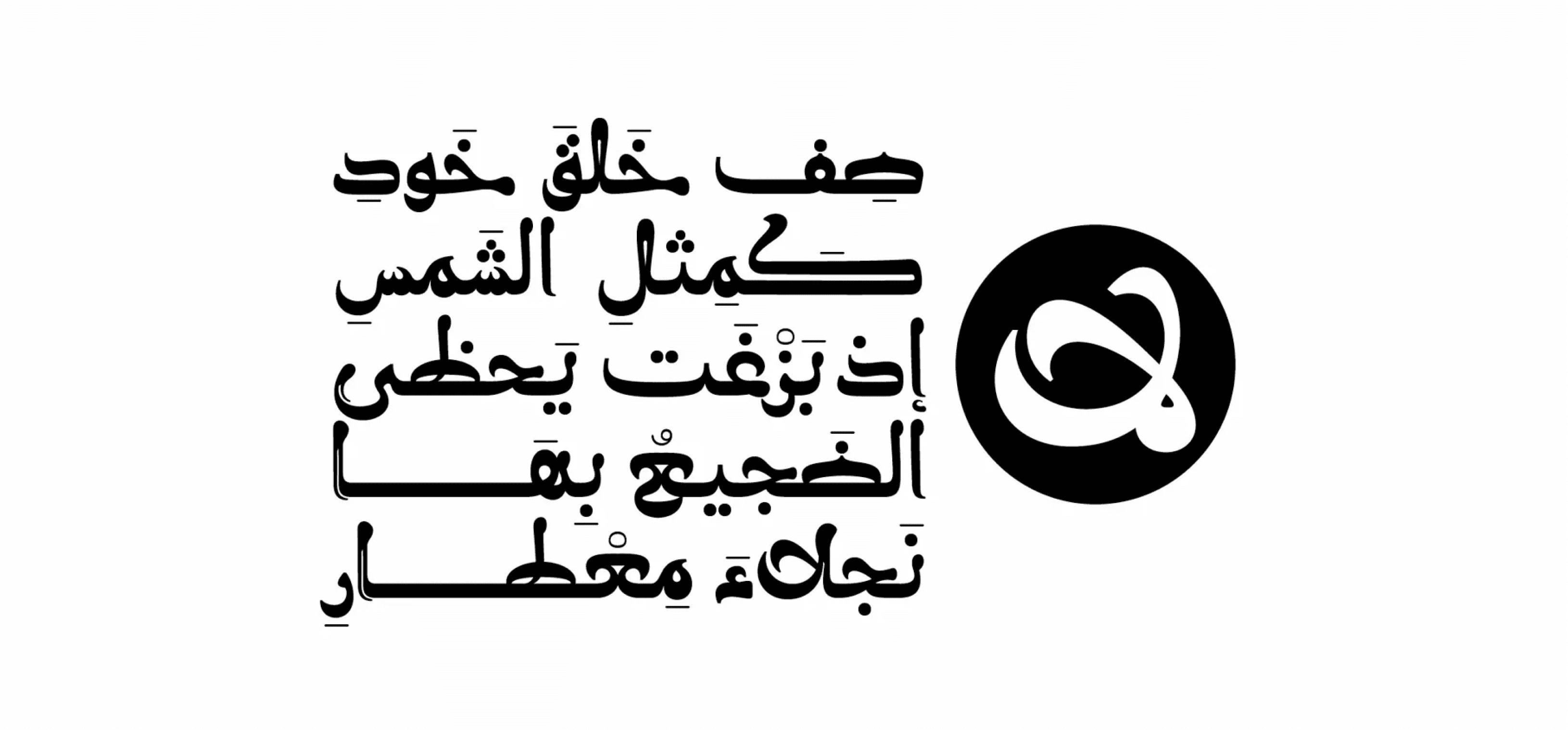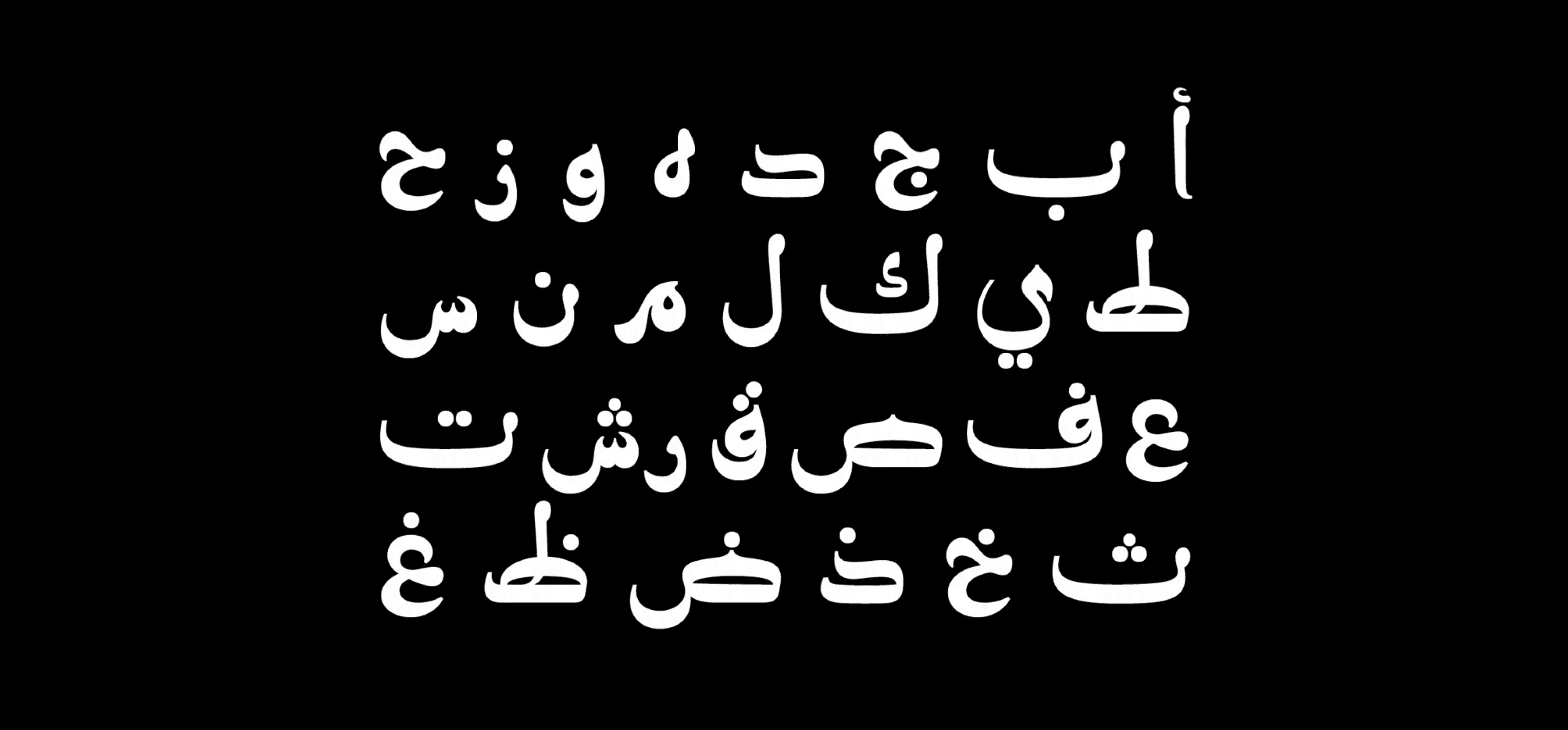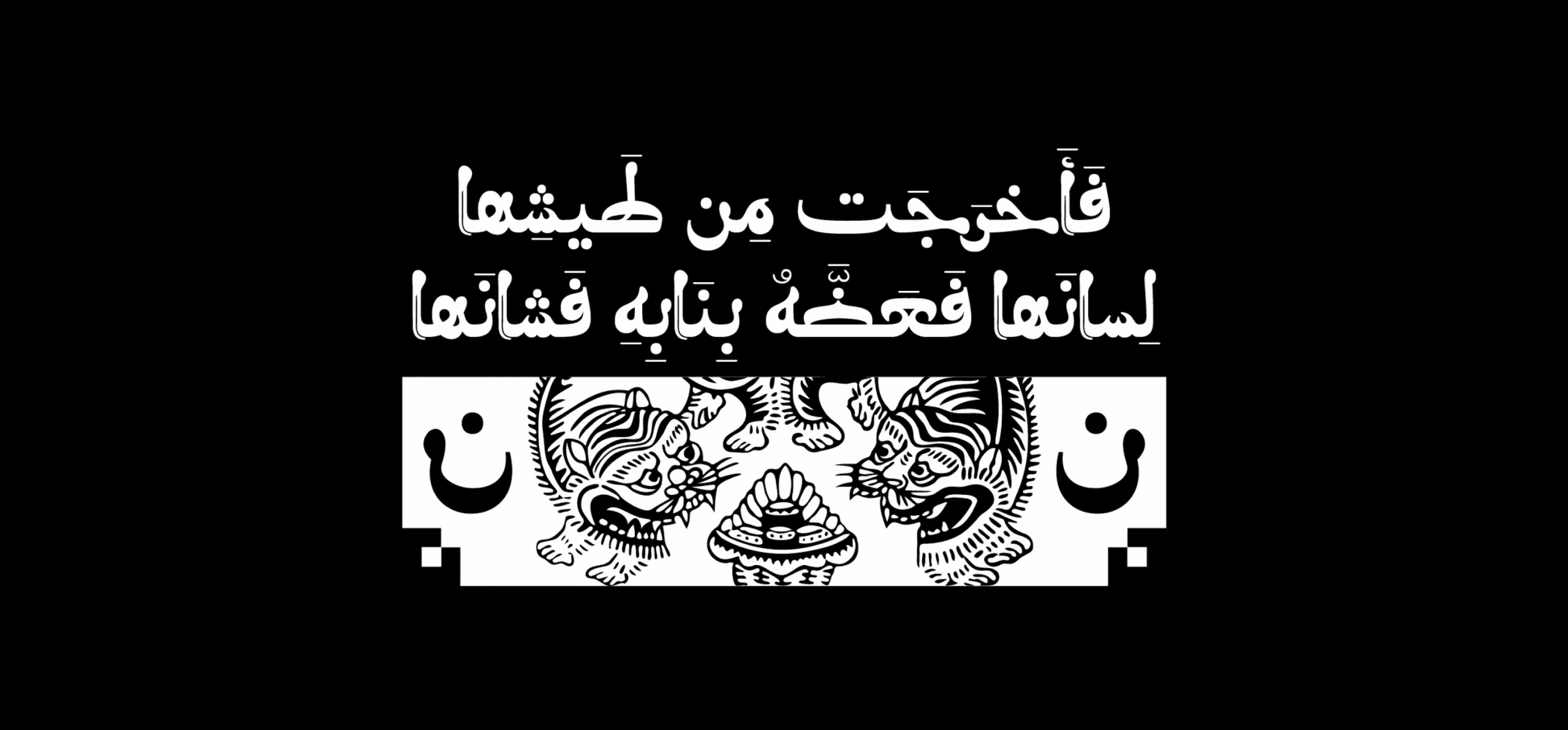
خط Molan (وتعني "مُليَّن" أو "مُطوَّع" بالعربية) هو خط عرض عربي يتميز بتصميم أنيق يجمع بين البنية الخطية شبه التقليدية واللمسة العصرية. يستوحي الخط شكله من الخط المغربي، مع دمج عناصر من خط النسخ، ما يمنحه توازنًا فريدًا بين الطابع التراثي والانسيابية الحديثة. يتناسب Molan مع مجموعة واسعة من المشاريع الإبداعية مثل تصميم المواقع، الإعلانات، الهويات البصرية، والمطبوعات. كما يتمتع بتوافق كامل مع أنظمة Windows وmacOS وتطبيقات الهواتف المحمولة، مما يجعله خيارًا عمليًا للمصممين الباحثين عن خط عربي يتمتع بالشخصية والمرونة.